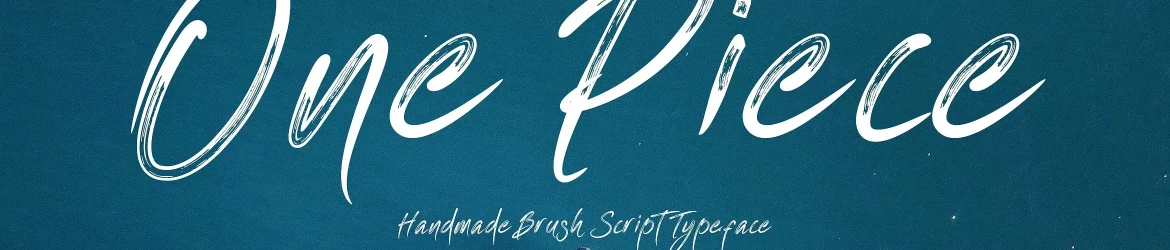
One Piece Brush Font – Fonte Grátis
One Piece Brush Font
A One Piece Font é uma aquarela script que surgiu dos pincéis, trazendo para seu design um estilo elegante e sofisticado. Seja você criando material para marcas, projetos de moda ou até mesmo para se conectar com o clima gótico, esse tipo de fonte oferece um toque urbanizado e atual. Com uma leitura fluida e interessante, é ideal para aplicar em diversas ideias: desde outdoors e embalagens, passando por headlines e postagem nas redes sociais, até assinaturas e sinalização. Esta fonte se destaca não apenas como um recurso para branding e projetos de moda, mas também como uma ferramenta versátil que pode ser usada em qualquer projeto que deseje adicionar aquele ar urbano, moderno e único à sua identidade visual.